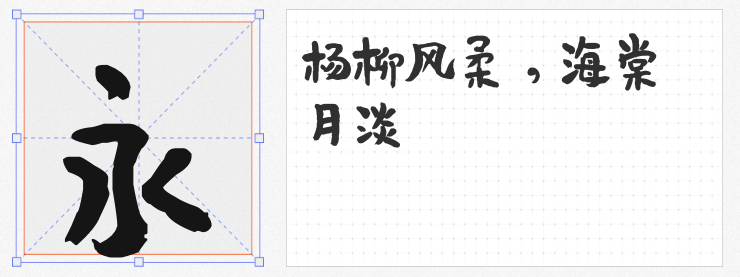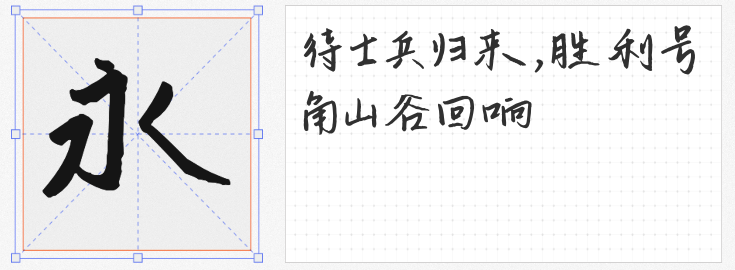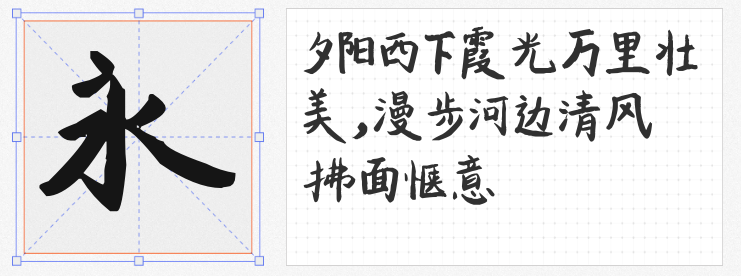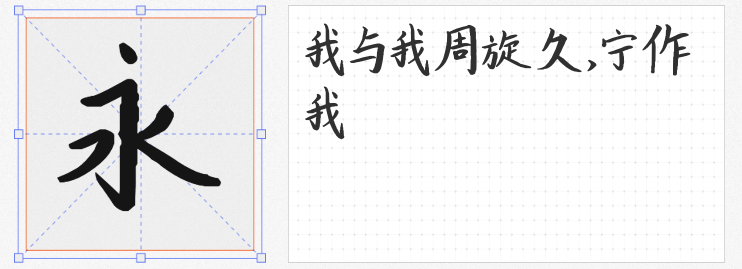
在商业设计中,手写字体的独特性与人文气息能为作品注入鲜活的生命力。今天推荐四款免费商用且风格迥异的手写字体。
1. 平方塞北体
这款字体以“浑厚”为核心,笔画粗壮如磐石,转折处自带重力感,仿佛用毛笔蘸满浓墨一气呵成。其强烈的视觉张力使其成为标题、海报的绝佳选择,尤其在影视游戏场景中,能瞬间营造出磅礴气势。无论是电商促销的醒目标语,还是包装设计的品牌主视觉,平方塞北体都能以力量感抓住观众眼球。
2. 平方将军体
笔触适中、结构稳重的平方将军体,既有书法的洒脱感,又不失现代设计的简洁性。其笔画粗细过渡自然,适合作为正文与标题的过渡字体,尤其在平面宣传、网页设计中,既能保证可读性,又能通过微妙的笔触变化提升设计质感。书法爱好者还可将其用于字帖临摹,感受笔锋的灵动韵律。
3. 平方刘昂乐天体
这款毛笔字体的精髓在于“粗细不均”的笔画与“飞白”效果,起笔如刀刻般刚劲,收尾却似墨色自然晕染,完美复刻了传统书法的书写痕迹。在印刷包装或广告海报中,它能瞬间传递出古朴典雅的东方韵味,尤其适合茶文化、国潮品牌等需要文化底蕴的场景,让文字成为传递情感的视觉符号。
4. 平方相思体
不同于前者的浓墨重彩,平方相思体以“均匀适中”的笔画和“完整规则”的结构,营造出清新脱俗的文艺气质。无论是社交媒体的文案排版,还是书籍封面的标题设计,它都能以柔和的视觉感传递温暖与治愈,尤其适合女性向、生活类品牌,让文字自带温柔滤镜。